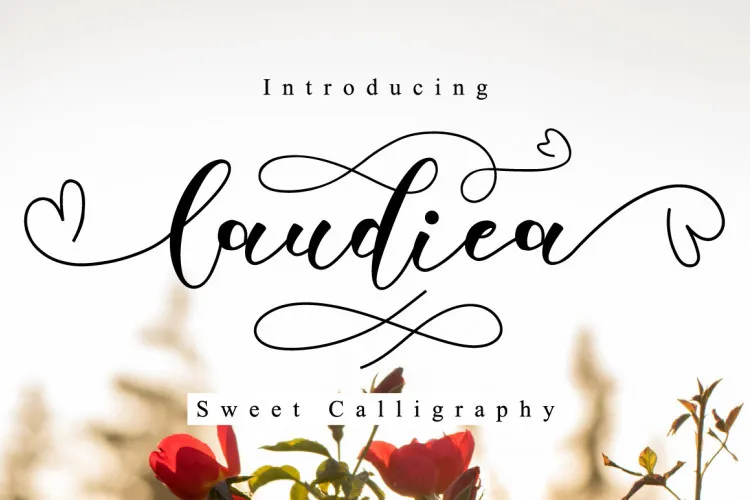
Laudiea Script Font – Download Grátis
Olha quem está aqui! Se você é fã de fontes escrita modernas com estilo atual da escrita, então a Laudiea Font Script vai ser definitivamente uma descoberta para você. Esta elegante e sofisticada font tem um design inovador que parece natural e é fácil de usar. Introduzimos a Laudiea Font Script, criado pelo designer m@graphics. Quer experimentar o toque manuscrito em seus projetos? A Laudiea Font Script pode ser perfeita para aplicação em projetos de marca, logotipos, eventos de casamento, postagens nas redes sociais, anúncios, embalagens de produto, designs de produtos, etiquetas, fotografia e até mesmo como fundo ou marcas na arte. É uma fonte que vai agregar um toque autêntico à sua obra! Laudiea Font Script é perfeita para designers que desejam dar um toque único aos seus projetos, seja para branding, logotipos de eventos, design do casamento, anúncios de produtos ou até mesmo trabalhos de fotografia. Essencialmente, a Laudiea Font Script é uma fonte para quem busca algo autêntico e moderno na sua arte. Então, quando você estiver procurando por um toque único que se alinha com o seu estilo próprio, a Laudiea Font Script é definitivamente uma escolha ótima.